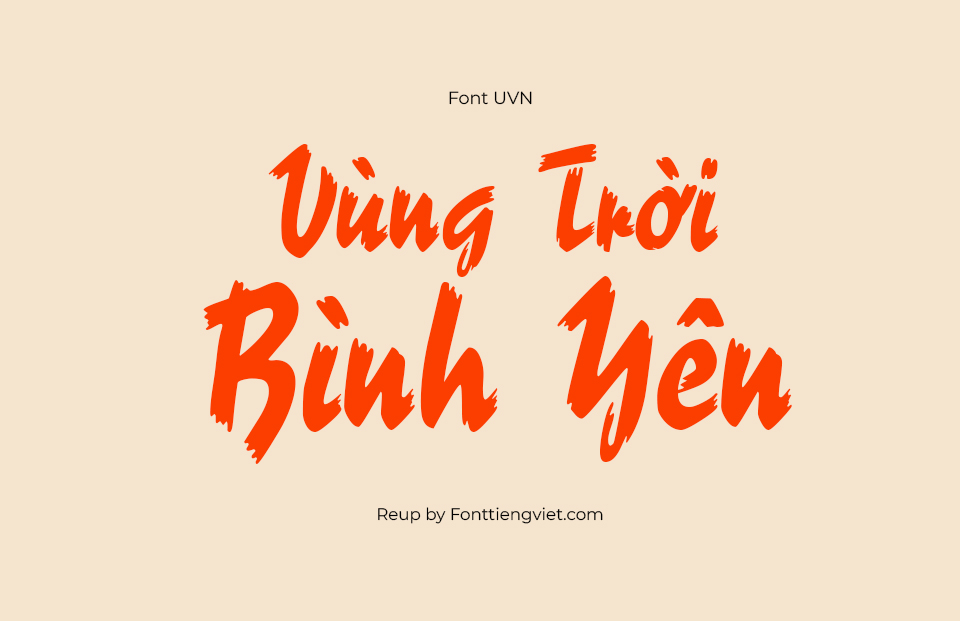
Font Việt Hóa UVN But Long 2
Giới thiệu về Font Việt Hóa UVN But Long 2
Trong thế giới thiết kế đồ họa, việc lựa chọn một Font Miễn Phí phù hợp đóng vai trò quan trọng trong việc truyền tải thông điệp. Font Việt Hóa UVN But Long 2 là một trong những bộ phông chữ thư pháp nổi tiếng, mang đậm nét văn hóa truyền thống Việt Nam. Với các đường nét uyển chuyển như được viết bằng bút lông thực thụ, bộ font này đã trở thành lựa chọn ưu tiên cho các dự án thiết kế mang tính nghệ thuật và giáo dục.
Đặc điểm nổi bật của Font Việt Hóa UVN But Long 2
Nét vẽ thủ công tinh tế
Điểm khác biệt của Font Việt Hóa UVN But Long 2 chính là sự mô phỏng chân thực các nét thanh, nét đậm của bút mực. Các ký tự được thiết kế với độ mềm mại cao, tạo cảm giác gần gũi và trang trọng. Điều này giúp các bài giảng điện tử hoặc thông báo tại nhà trường trở nên sinh động và thu hút học sinh hơn.
Tương thích và tối ưu hóa
Ứng dụng thực tế trong học đường
Nhờ vẻ ngoài thanh lịch, font chữ này thường được dùng để thiết kế bằng khen, thiệp mời sự kiện hoặc các tiêu đề báo tường. Sự kết hợp giữa yếu tố truyền thống và hiện đại giúp các sản phẩm thiết kế luôn giữ được giá trị thẩm mỹ cao.